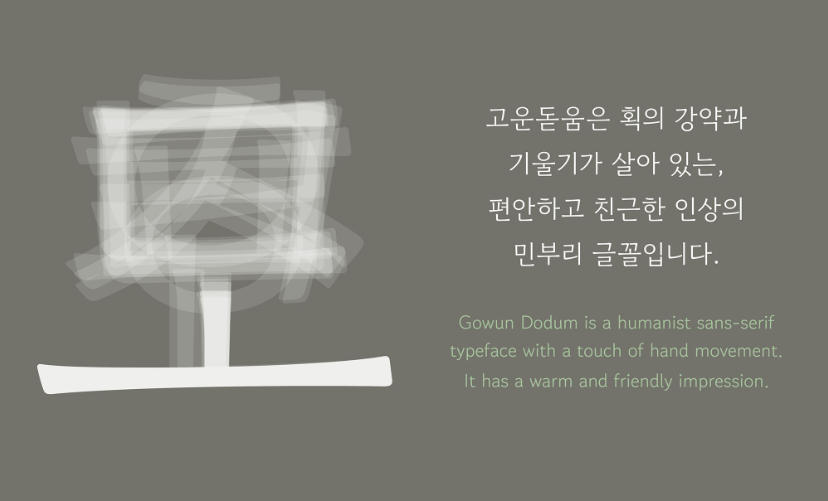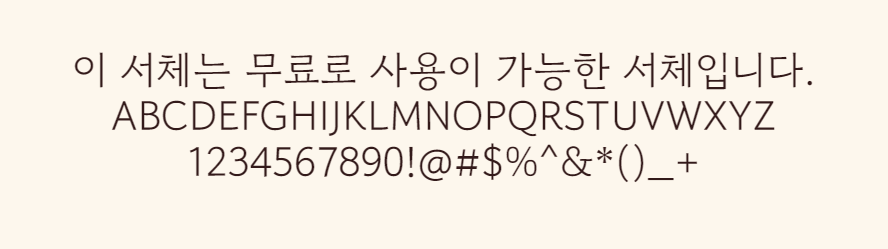
고운돋움
고운돋움체(Gowun Dodum)는 손글씨의 따뜻함과 현대적인 세련미를 결합한 휴머니스트 산세리프 서체로, 가독성이 높아 다양한 디자인 작업에 적합합니다. 펜으로 쓴것같은 느낌의 정갈한 돋움체를 표현하였습니다.
제작 이유 및 형태적 특징
고운돋움체는 손글씨의 따뜻함과 현대적인 세련미를 결합한 휴머니스트 산세리프 서체로, 가독성이 높아 다양한 디자인 작업에 적합합니다.
사용 용도
고운돋움체는 손글씨의 따뜻함과 현대적인 세련미를 결합한 휴머니스트 산세리프 서체로, 가독성이 높아 다양한 디자인 작업에 적합합니다.
서체 미리보기